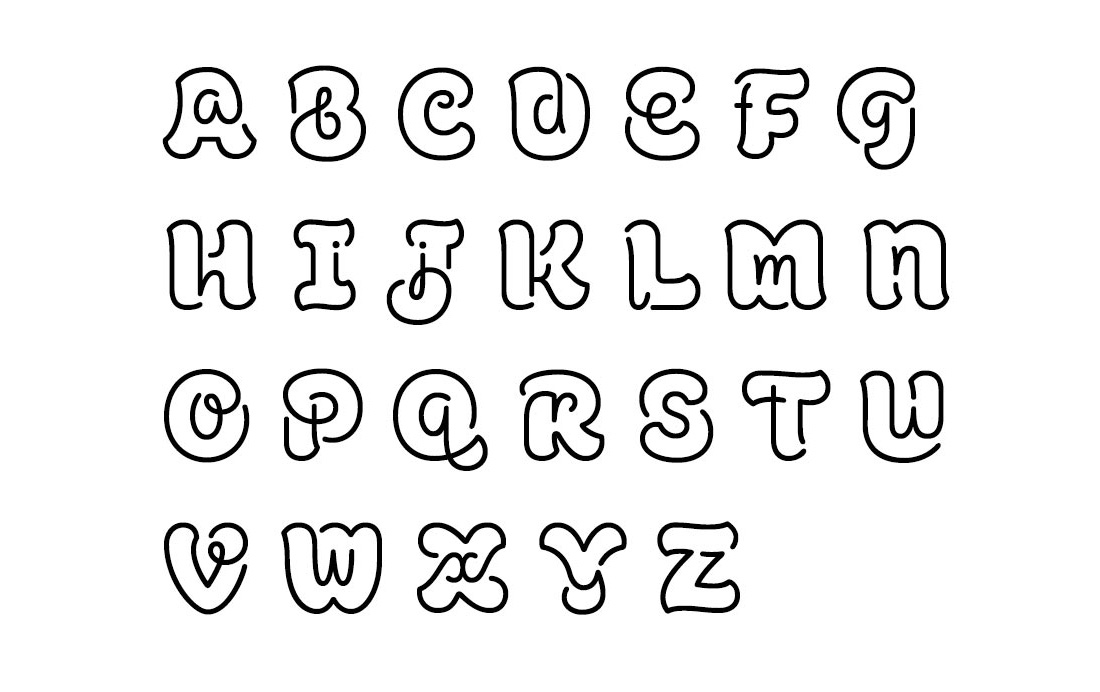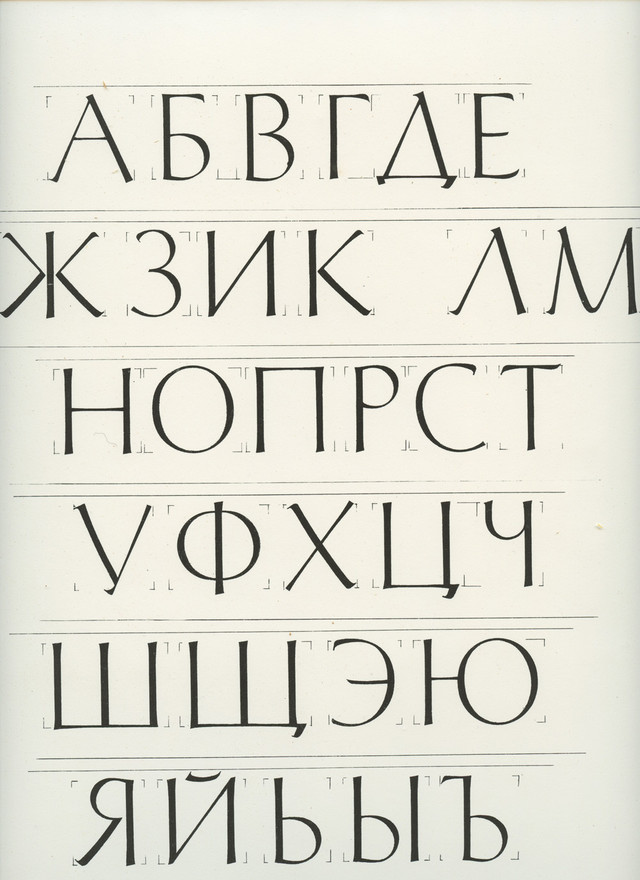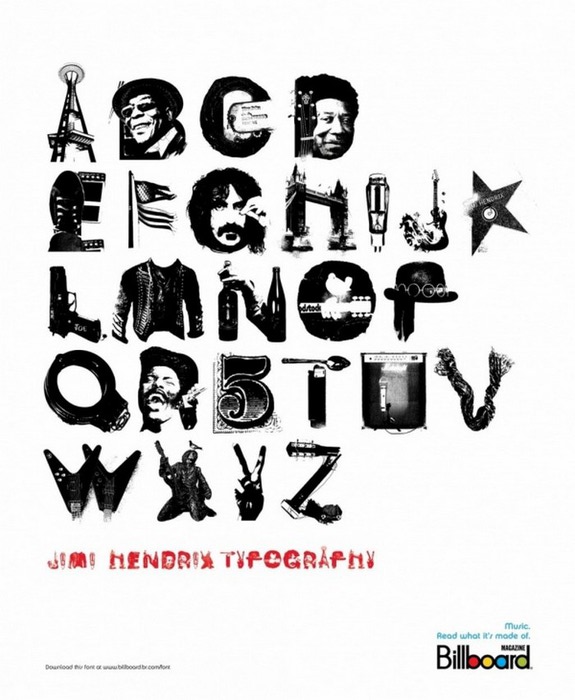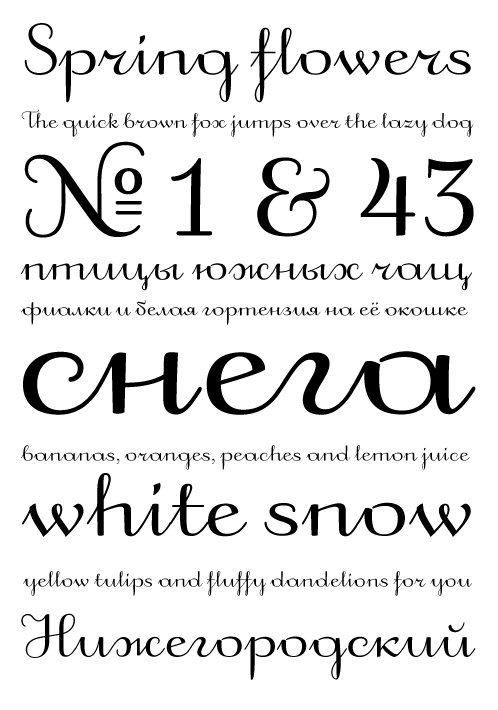
Узнаем что это — акцидентные шрифты. Дизайн и предназначение
Акцидентные шрифты предназначены для использования в заголовках больших размеров. Потому они часто имеют более заметный и выделяющийся дизайн, чем простые, относительно «сдержанные» шрифты, которые обычно используются для основного текста. В немецком языке существует термин akzidenzschrift, что означает коммерческий или торговый шрифт, который используется для заголовков и не предназначен для основного текста. Этим словом как раз и обозначается то, для чего используют акцидентные шрифты. Знаменитое название шрифта «Акциденц Гротеск», что буквально означает «коммерческий без засечек», происходит именно от этого термина.
История появления
Акцидентные шрифты — это способ привлечь внимание к какой-то части текста, потому для их создания могут использоваться не только начертание обычных букв, но и знаки, нарисованные от руки, каллиграфия и различные абстрактные или рисованные стили. Для них обычно используется размер кегля от 14 пунктов.
Лучшие текстовые шрифты легко читать в длинных абзацах. Они не привлекают к себе особого внимания и были спроектированы так, чтобы лучше всего работать между кеглем в 6 и 14 пунктов.
Акцидентные шрифты — это относительно недавнее изобретение. Они используются для того чтобы привлечь читателя к тексту, создать настроение или объявить важную информацию. В них не было необходимости до конца XVIII века, в это время появились рекламные плакаты. До этого времени гарнитуры, не предназначенные для основного текста, выглядели как обычные буквы.
Появление плакатов и более широкое использование вывесок стимулировало появление новых видов шрифтов. В то же время в начале XIX века начали появляться новые дизайны букв, с засечками, но гораздо более смелые по дизайну. Шрифты без засечек уже использовалось в нестандартных надписях. Но они почти не применялись для печати до 1830-х годов.
Первые акцидентные шрифты — это чрезвычайно жирные и сжатые гарнитуры, которые использовались, чтобы привлечь внимание.
Кроме того, некоторые из них, такие как Cochin и Koch-Antiqua, имели особую конструкцию с небольшой высотой x. Акцидентные шрифты, дизайн которых был приближен к этим гарнитурам, был очень популярен в начале XX века.
Современные технологии и их влияние
Благодаря появлению методов фотонабора и цифровой печати, позволяющим набирать шрифты любого размера, стало возможным использовать акцидентные шрифты в ситуациях, когда обычно применяются рукописные надписи, например, на деловых логотипах. Многие современные семейства цифровых шрифтов, такие как Neutraface, Neue Haas Grotesk и Arno, включают в себя как обычные текстовые стили, так и дополнительные, с более лаконичным дизайном.
Стили отображения шрифта
Акцидентные шрифты, предназначение которых — привлекать внимание, могут выглядеть как надписи с рисунком, например, с использованием штрихов, похожих на ручное письмо. Они могут быть затемненными или гравированными, с пробелами в центре, предназначенным для рельефных трехмерных букв.
Еще один вариант — заштрихованные изображения, которые выглядят серыми при просмотре на расстоянии.
Существуют также необычные или абстрактные редизайны алфавита, надписи, которые кажутся поврежденными или искаженными, такие как Shatter или Electric Circus. К акцидентным шрифтам относятся и некоторые сверхлегкие и смелые адаптации обычных буквенных форм, в том числе Cooper Black или Gill Kayo. А при помощи смеси заглавных и строчных букв можно создать необычный эффект.
Особенности оформления
Многие шрифты имеют различное настроение или индивидуальность. Они могут быть серьезными, вычурными, игривыми, элегантными. Настроение шрифта должно соответствовать цели дизайнера. Например, закругленная гарнитура с пузырьками и шариками подойдет для приглашения на день рождения ребенка, но не для деловой новостной рассылки. Как это часто бывает с людьми, противоположности, как правило, притягиваются: «интровертированные» и «экстравертные» шрифты прекрасно сочетаются друг с другом.
Поэтому, если у дизайнера есть отличительный шрифт с «сильной индивидуальностью», его можно соединить с чем-то более нейтральным и консервативным для сбалансированного оформления.
Применение гарнитур
Акцидентные шрифты бывают обратно-контрастными. Это означает, что в них инвертируются контраст обычного письма, а горизонтальные штрихи сделаны толще, чем вертикальные. Надписи могут включать в себя использование трафаретных или тисненых ленточных шрифтов для промышленной эстетики. Рестораны часто предпочитают «симуляцию» гарнитуры, предназначенной для другой системы письма. Более прозаический стиль акцидентных шрифтов — это те, которые предназначены для вывесок, такие как Johnston, Highway Gothic, Transport и Clearview. У них часто есть особенности, позволяющие увеличить удобочитаемость. Например, у Johnston и Transport есть загнутая буква L в нижнем регистре, чтобы отличить его от i в верхнем регистре.
Фокус внимания пользователя
Читабельность гарнитуры очень сильно зависят от размера букв.
Например, в шрифтах с засечками тонкие части пропорционально утяжеляются с уменьшением размера. Если бы им оставляли ту же жирность, что и для больших размеров, контраст между толстыми и тонкими штрихами был бы слишком велик, что затрудняло бы чтение текста. Акцидентные шрифты — это более крупная гарнитура, обладающая особой индивидуальностью.